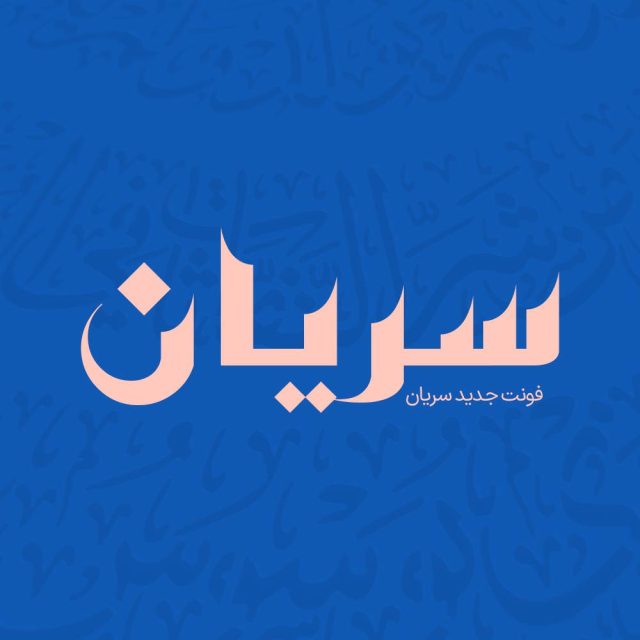
فونت فارسی سِریان Seryan Font
فونت فارسی سِریان از دسته فونت های کوفی است. از این فونت می توان برای طراحی لوگو، طراحی اسم، دیوار نوشتههای هنری و مذهبی، طراحی بنر، طراحی پوستر و غیره استفاده کرد و این به جهت شکستگیها و انحناهای متعادل، همنشینی روان حروف در کنار هم، حجم دهی بالا و اتصالات مختلف است.
پیشنمایش و نمونه تایپ های فونت سِریان